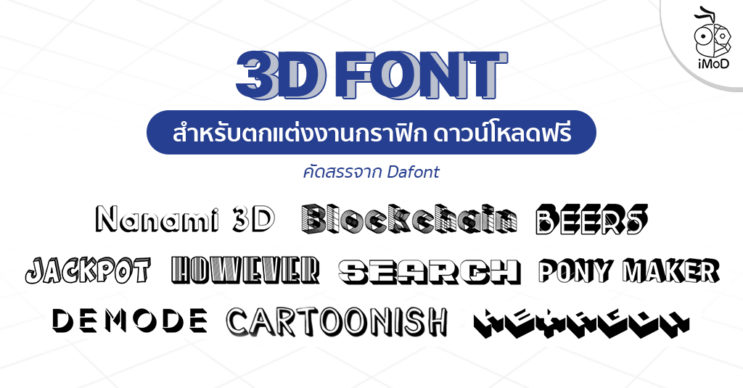
รวม 3D Font ภาษาอังกฤษ คัดสรรมาให้ดาวน์โหลดฟรี จาก Dafont
1. Jackpot [ดาวน์โหลดที่นี่]
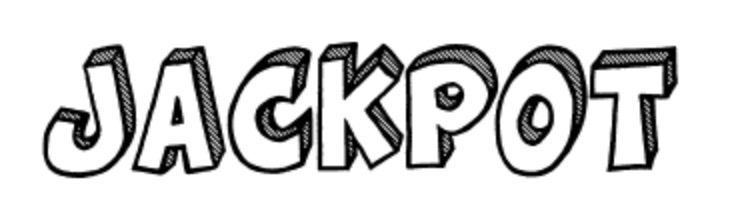
2. Blockchain [ดาวน์โหลดที่นี่]
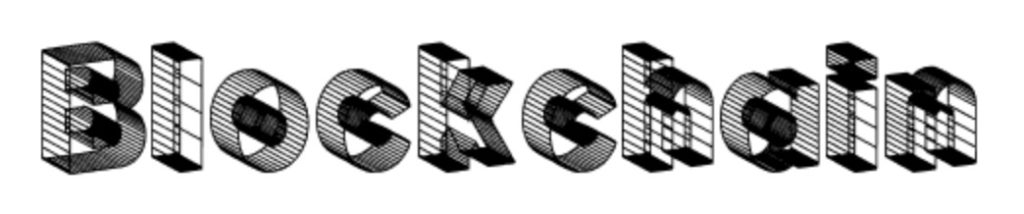
3. Nanami 3D [ดาวน์โหลดที่นี่]
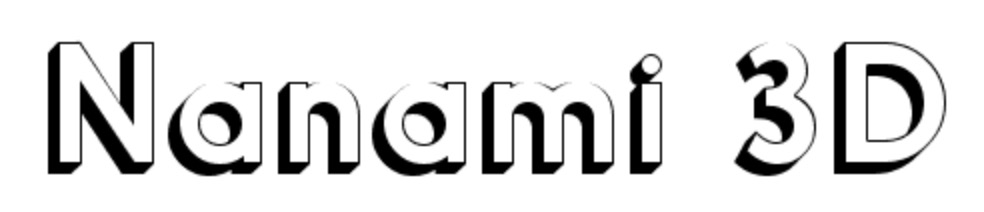
4. Pony Maker [ดาวน์โหลดที่นี่]
5. However [ดาวน์โหลดที่นี่]
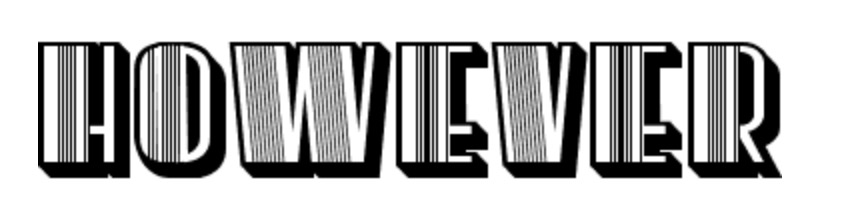
6. Beers [ดาวน์โหลดที่นี่]
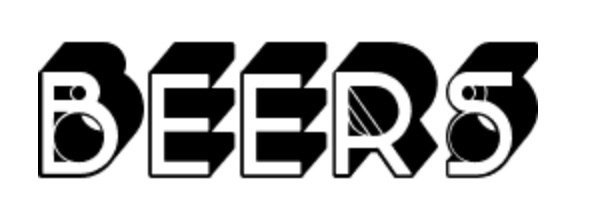
7. Hexagon [ดาวน์โหลดที่นี่]
8. Demode [ดาวน์โหลดที่นี่]
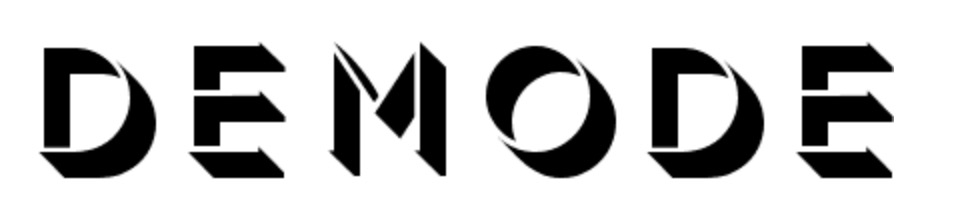
9. Search [ดาวน์โหลดที่นี่]
10. Cartoonish [ดาวน์โหลดที่นี่]